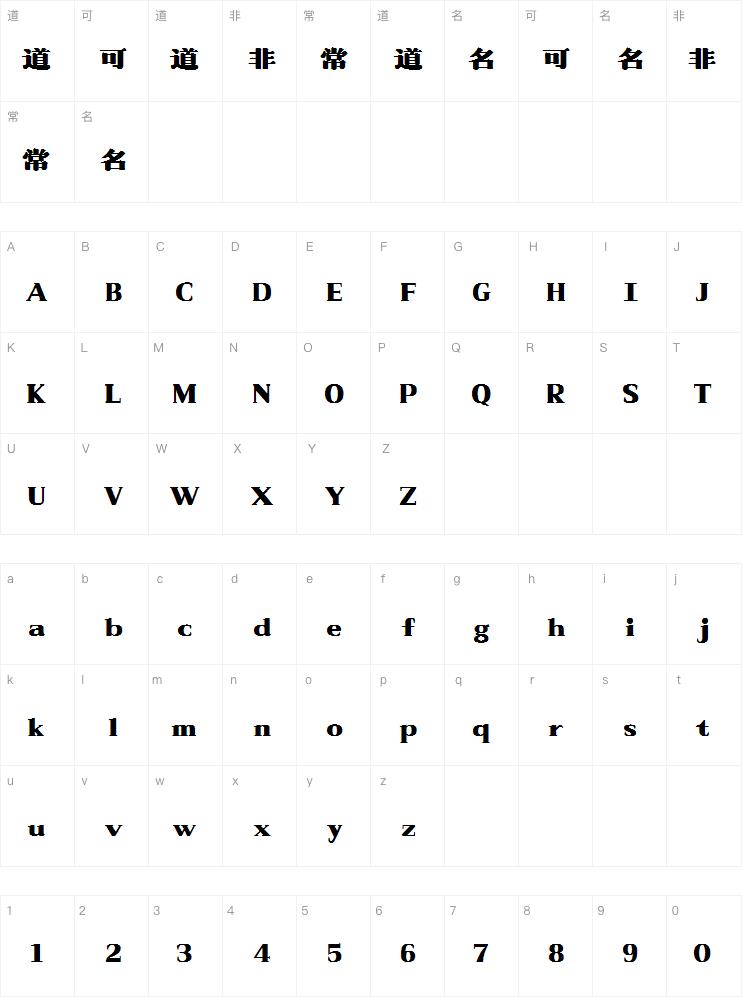
山海温润宋w
山海温润宋,是一款全新的字体,包含汉字9169个,符号200+个。该字体是一款温润尔雅的宋体字。该字体秀雅端庄,字形略宽,呈现出一种厚实稳重、气息舒展,又颇具人文气质的面貌;该字体特别重视字形轮廓曲线的质感:布点简练、轮廓丝滑如玉,彰显简约之美;笔画多取圆润弧线设计,结构严谨,看上去赏心悦目,温润尔雅。作为一款宋体标题字,结构清晰易读,有着非常强的识别性。从整体结构来看,这款字体均衡稳固,重心偏高,中宫内敛。给人稳定、可靠的感觉。在秉承笔形间创新,结合当代设计视觉环境,融入现代审美,适用场景更多元,笔画造型清晰锐利,删繁取简,速度感强,端庄秀丽,完美地呈现出该字体的温润。